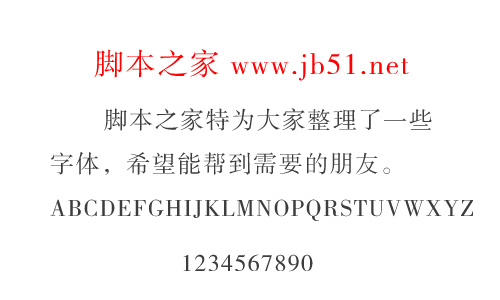
方正書宋簡體字體是方正字體庫中的一種字體,方正書宋源自上海印刷技術(shù)研究所的宋二,原字形距今已有近60年。最初的設(shè)計就是專門針對最常用的小字號正文排版。方正書宋的字形端正清秀,中宮適度。憑著清晰爽目、久讀不易疲勞、印刷適性好的優(yōu)點,長期被作為雜志和書籍的正文首選字體,所以也是一款非常經(jīng)典的正文宋體。喜歡的朋友們可以前來下載使用。